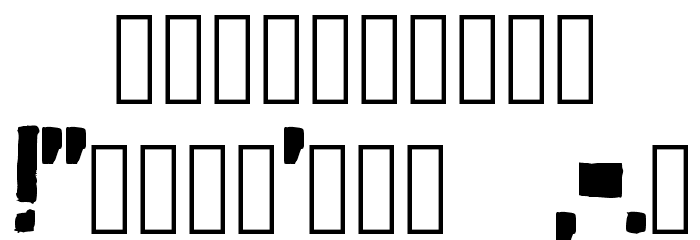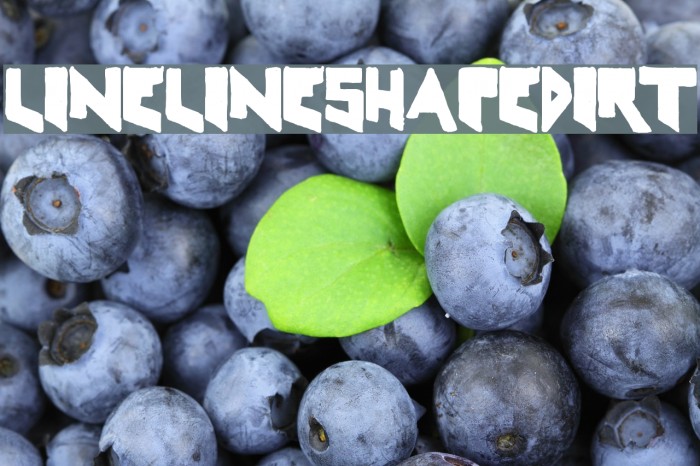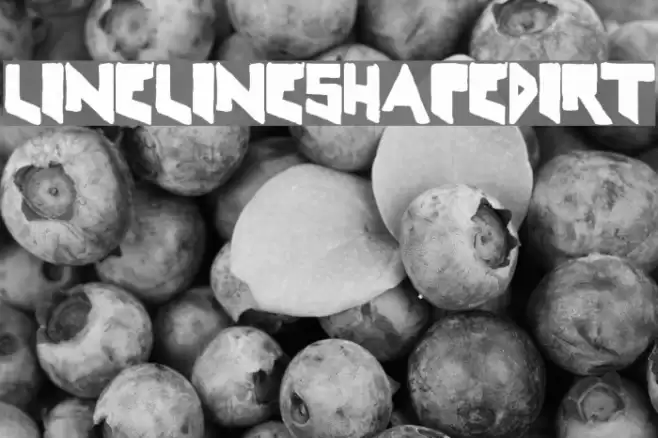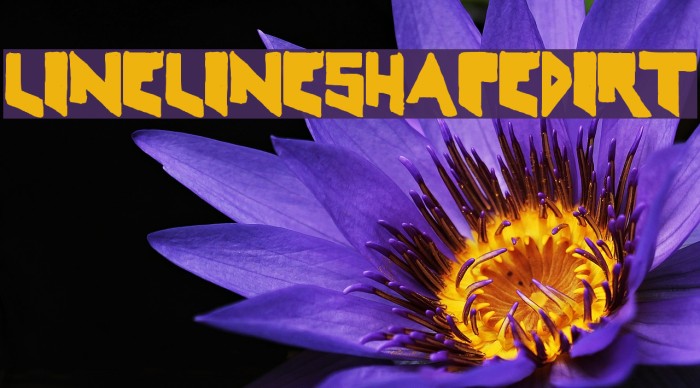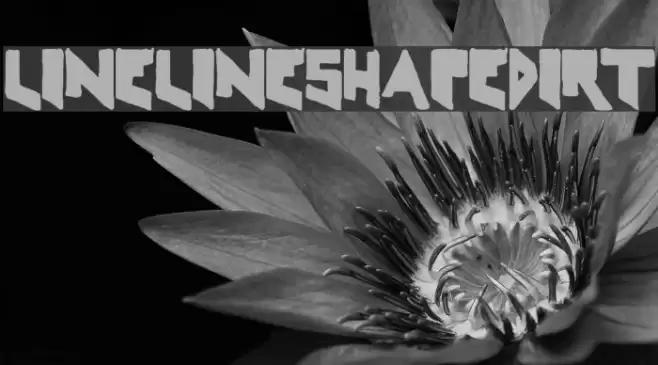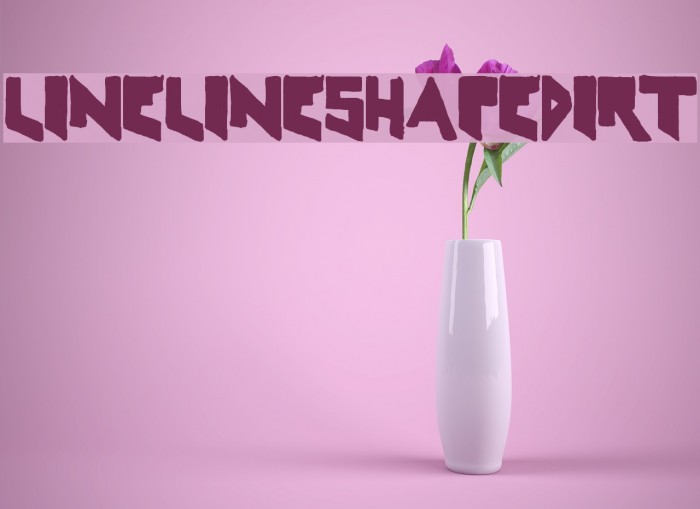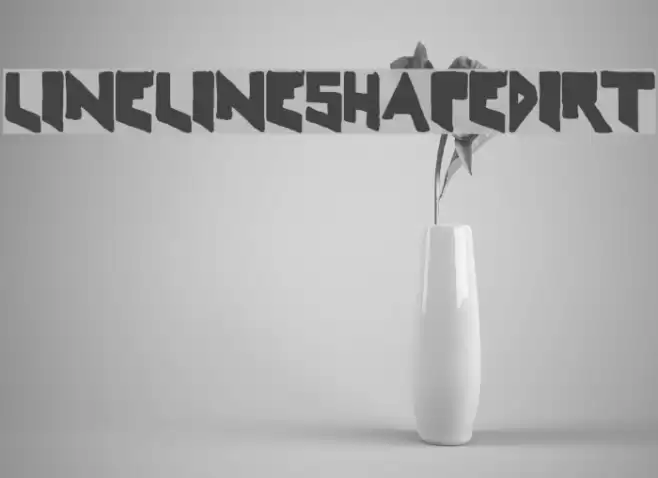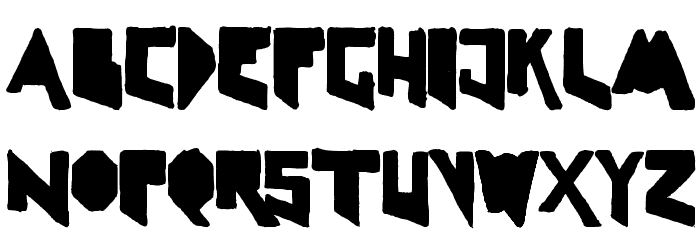
LineLineShapeDirty Font
| समग्र शैली | Modern, Edgy |
| उपयोग का मामला | Headlines, Logos, Posters |
| सुझाए गए प्रोजेक्ट | Ideal for posters, album covers, streetwear branding, and any project needing a bold, edgy aesthetic. |